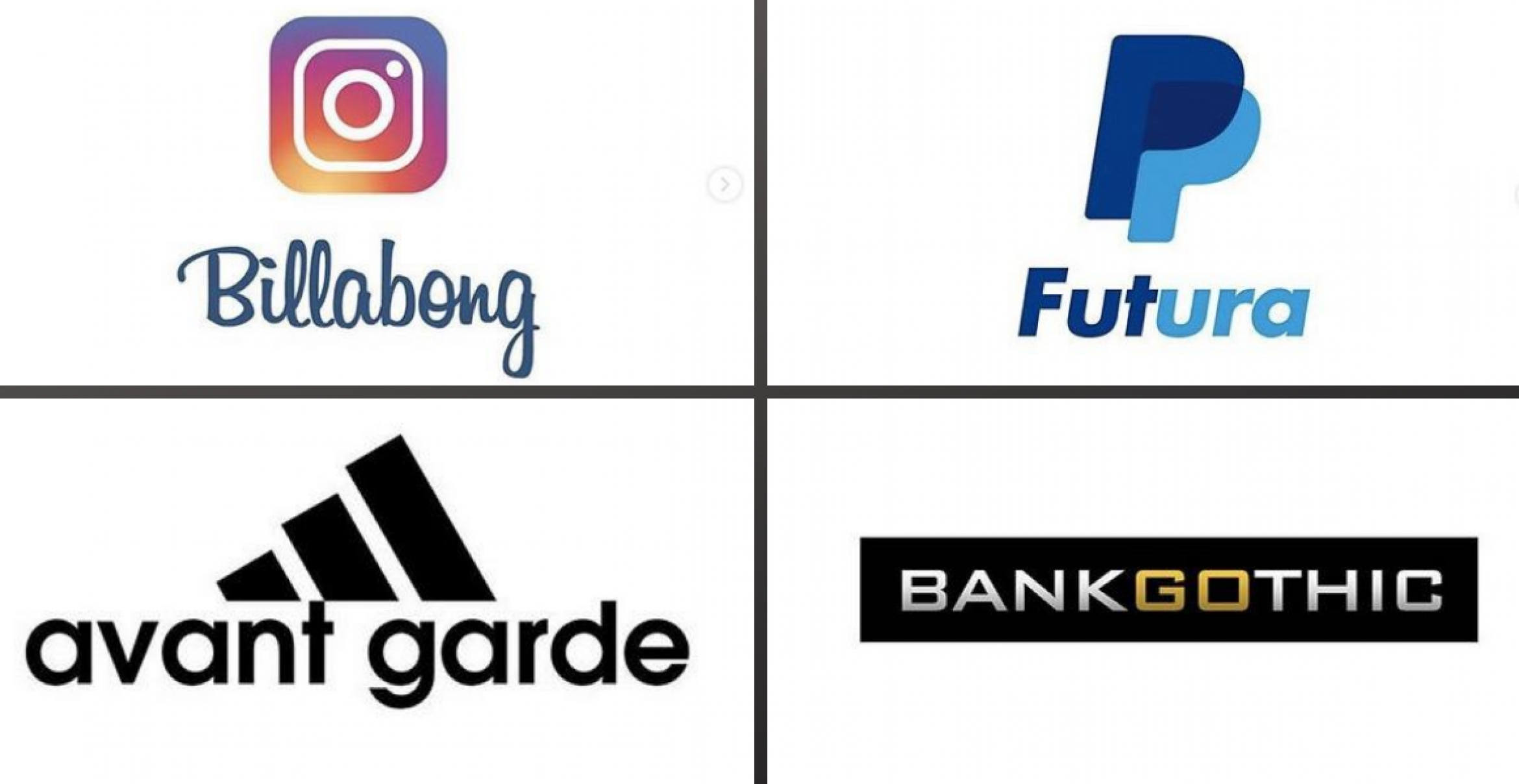
Ein Grafikdesigner analysiert, welcher Font für welches Logo verwendet wurde
Ein Logo muss zur Marke passen, hohen Wiedererkennungswert haben und Emotionen wecken. Daher lautet bei dem Design des Logos eine der Kernfrage immer: Welche Schriftart soll es denn sein?
Überraschenderweise greifen viele weltberühmte Marken zu bereits bestehenden Fonts und werkeln dann ein bisschen daran herum, wie der italienische Grafikdesigner Emanuele Abrate mit seinem Instagram-Account @logo_fonts aufdeckt.
„Die meisten bekannten Logos verwenden einen benutzerdefinierten Font (von Grund auf neu entworfen oder aus einem bereits bestehenden Font, um ihn anzupassen). Mein Ziel ist es, herauszufinden, welche Schriftart zu Beginn verwendet wird“, erklärt Abrate gegenüber Bored Panda sein Projekt.
Inzwischen hat er schon ca. 150 Fonts ermittelt, von Adidas und Nike über Instagram, Pornhub und Netflix bis Linkedin und Paypal.
Am häufigsten wird augenscheinlich Helvetica verwendet. Der Font wurde in der Schweiz entwickelt und 1957 veröffentlicht. Schnell wurde er die Hausschrift von Unternehmen wie Lufthansa, Deutsche Bahn, BMW oder BASF. International bekannt wurde er, als Apple Helvetica als Systemschrift von Apples Betriebssystem Mac OS einsetzte. Kein Wunder also, dass sich viele Firmen auf ihn stützen.